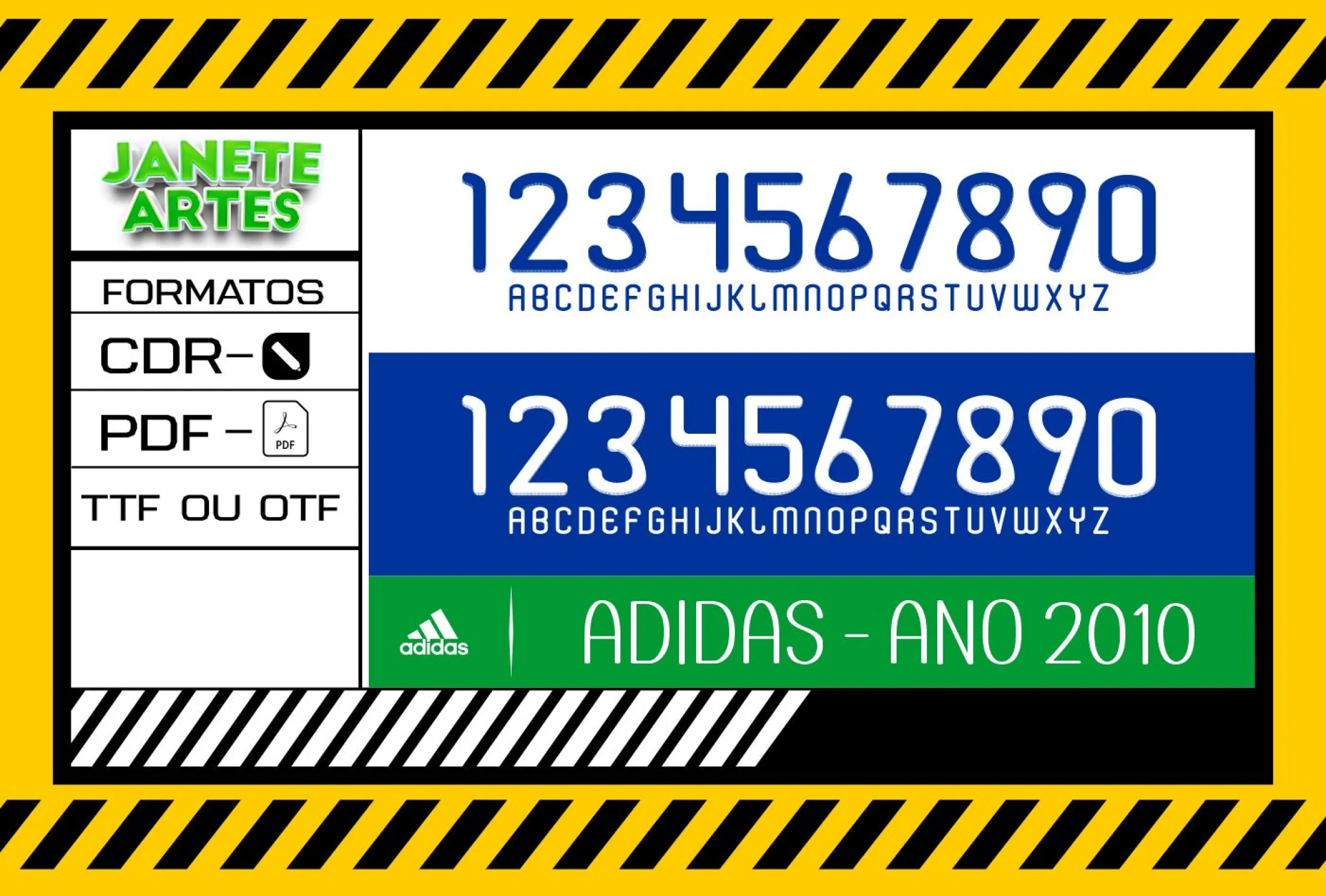
Camiseta unissex preta com logo no peito e estampa grande nas costas com design fonte de time tipografia Adidas 2010, perfeita para fãs de esportes e estilo urbano.
Fonte de Time Tipografia Adidas 2010
A fonte de time Tipografia Adidas 2010 traz um estilo único para suas camisetas, perfeito para criação de designs esportivos personalizados com visual autêntico e marcante.
Uma Jornada no Estilo Adidas 2010
Imagine a história de Lucas, um fã de futebol que sempre sonhou em ter uma camiseta personalizada com a fonte que marcou a década de 2010 da Adidas. Ele quis criar algo exclusivo para usar com os amigos no campeonato local. Com a Arte Fonte de Time Tipografia Adidas 2010 para Camisetas, ele conseguiu reproduzir aquele estilo clássico e esportivo que tanto admirava, levando seu visual para outro nível e chamando a atenção onde passava.
Dicas para Combinação e Aplicação
Com o Arte Fonte de Time Tipografia Adidas 2010 para Camisetas, você tem em mãos um design esportivo, autêntico e fácil de aplicar para dar um visual cheio de personalidade às suas peças. Aproveite para criar momentos inesquecíveis com estilo, conforto e muita inspiração!